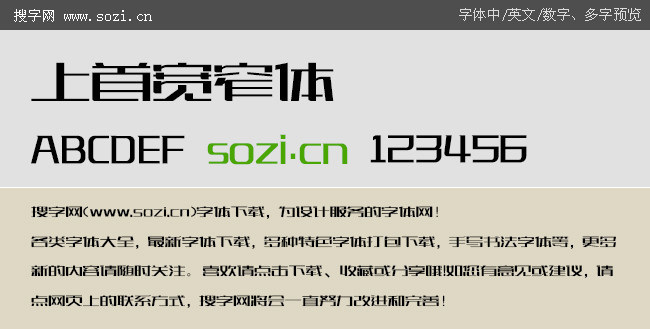
上首寬窄體
搜字網(wǎng)給大家提供一款上首寬窄體中文字體下載,上首寬窄體,字體風(fēng)格穩(wěn)重呈方塊形,粗壯的豎筆畫給人一種穩(wěn)重感,搭配細(xì)小的橫筆畫,二者相結(jié)合,產(chǎn)生一種協(xié)調(diào)美,是此套字庫的亮點。字庫整體特征有力、又參雜著柔和,具有現(xiàn)代、國際化的指向性,適用于搭配標(biāo)志、廣告標(biāo)語、商業(yè)廣告等高端屬性。